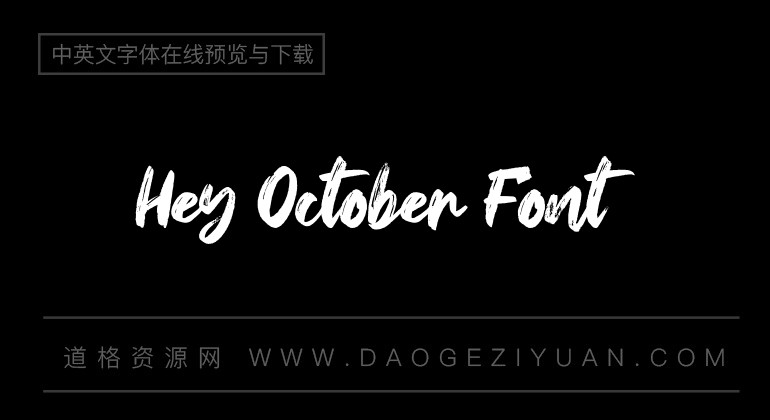
Hey October Font
Hey October Font是一种手写风格的字体,设计师为它注入了一些粗糙和不规则的笔画,使得这种字体看起来非常自然和放松。它的字母非常有个性,包含了很多自然的手写元素,如一些笔画的锯齿和抖动,这些特点使得Hey October Font在设计上非常具有表现力。 Hey October Font适用于各种设计场合,特别是一些需要突出文字个性的设计。例如,用于品牌logo、包装设计、海报或其他需要吸引人眼球的设计。它有多种字重和风格可供选择,包括常规、粗体、斜体等,可以根据自己的需要进行选择。
Hey October Font是一款非常不错的手写艺术字体,具有很好的视觉感,适合于文化类的宣传设计、商业类品牌的广告和产品包装设计以及个性化文字排版等较多场景。